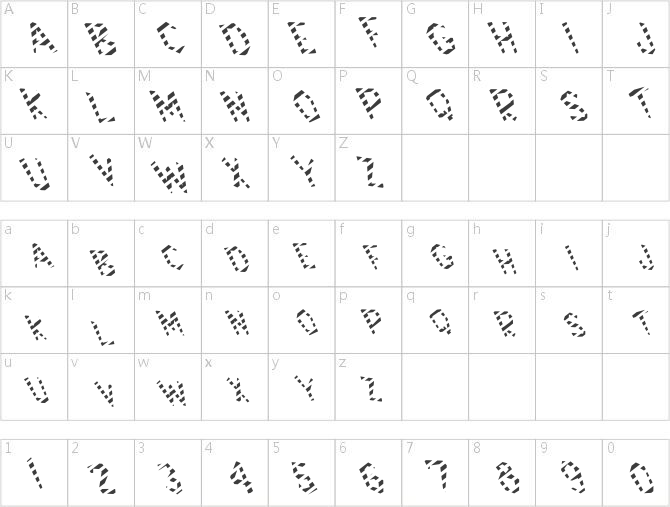
FZ JAZZY 8 STRIPED LEFTY 詳情頁(yè)
FZ JAZZY 8 STRIPED LEFTY字體字庫(kù)是一款讓人賞心悅目、百看不厭的英文字體,適合各類廣告和產(chǎn)品包裝設(shè)計(jì)應(yīng)用,字體大小0.04MB,格式為ttf字體,上傳用戶是釜源貿(mào)易,作者/版權(quán)方為未知